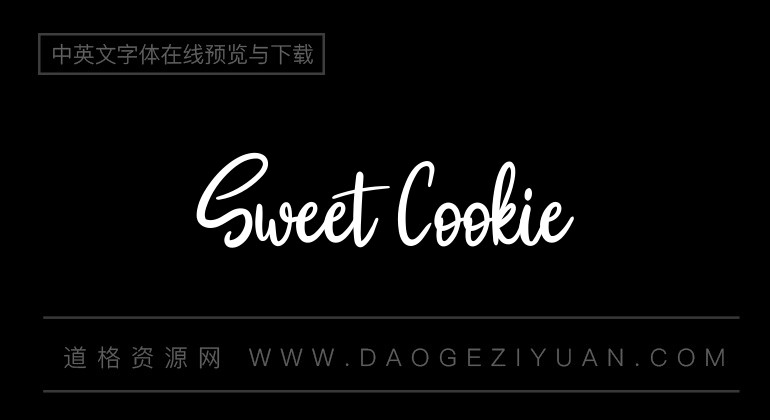
Sweet Cookie
Sweet Cookie 字体是一款手写风格的楷体字体,它拥有温暖、柔和的外观,适合用于标题、标签、logo等场景,能够给设计师带来更多的创意空间。Sweet Cookie字体拥有超过500个字符,可以满足多种语言的需求,支持多种格式,如OTF、TTF、WOFF等,可以满足不同平台的需求。
Sweet Cookie是一款非常不错的手写艺术字体,具有很好的视觉感,适合于文化类的宣传设计、商业类品牌的广告和产品包装设计以及个性化文字排版等较多场景。